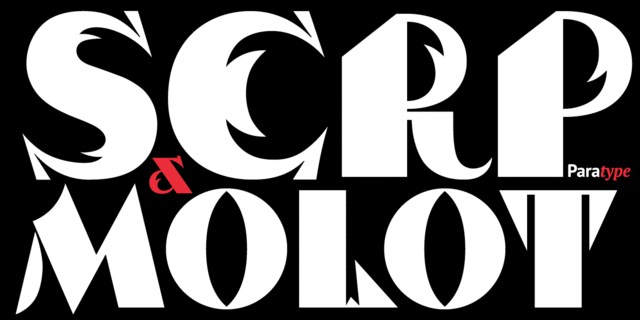
Шрифт разработан для фирмы ParaType в 2003 году (дизайнер Тагир Сафаев). Его рисунок основан на формах кириллических букв Сергея Чехонина (1878-1936). Чехонин принадлежал к движению 'Мир искусства', которое ассоциируется с расцветом книжного и театрального дизайна в России в начале ХХ века. Применяется в рекламе и акциденции. Шрифту Серп и Молот присужден диплом 'За совершенство в дизайне шрифта' на Международном конкурсе шрифтового дизайна ATypI 'буква:раз!', 2001.